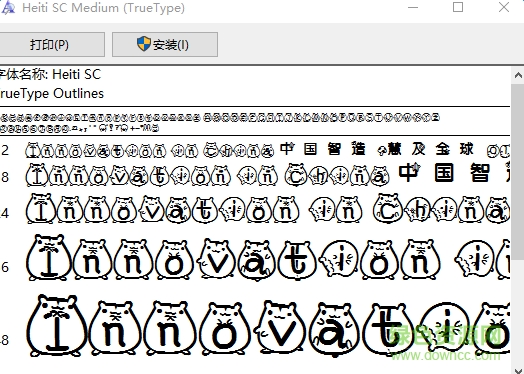
兒童可愛字體是一款很好看的電腦個性字體,就像這款字體的名字所寫那樣這款字體是很可愛的,寫出來的字形上面還會有漂亮的小裝飾,所以就會顯得這款字體很有特色,喜歡的朋友可以來綠色資源網(wǎng)下載。
兒童可愛字體是一款很有特色又很實用的電腦字體,用于藝術(shù)設(shè)計、廣告設(shè)計等方面都是很不錯的,歡迎大家來綠色資源網(wǎng)下載。